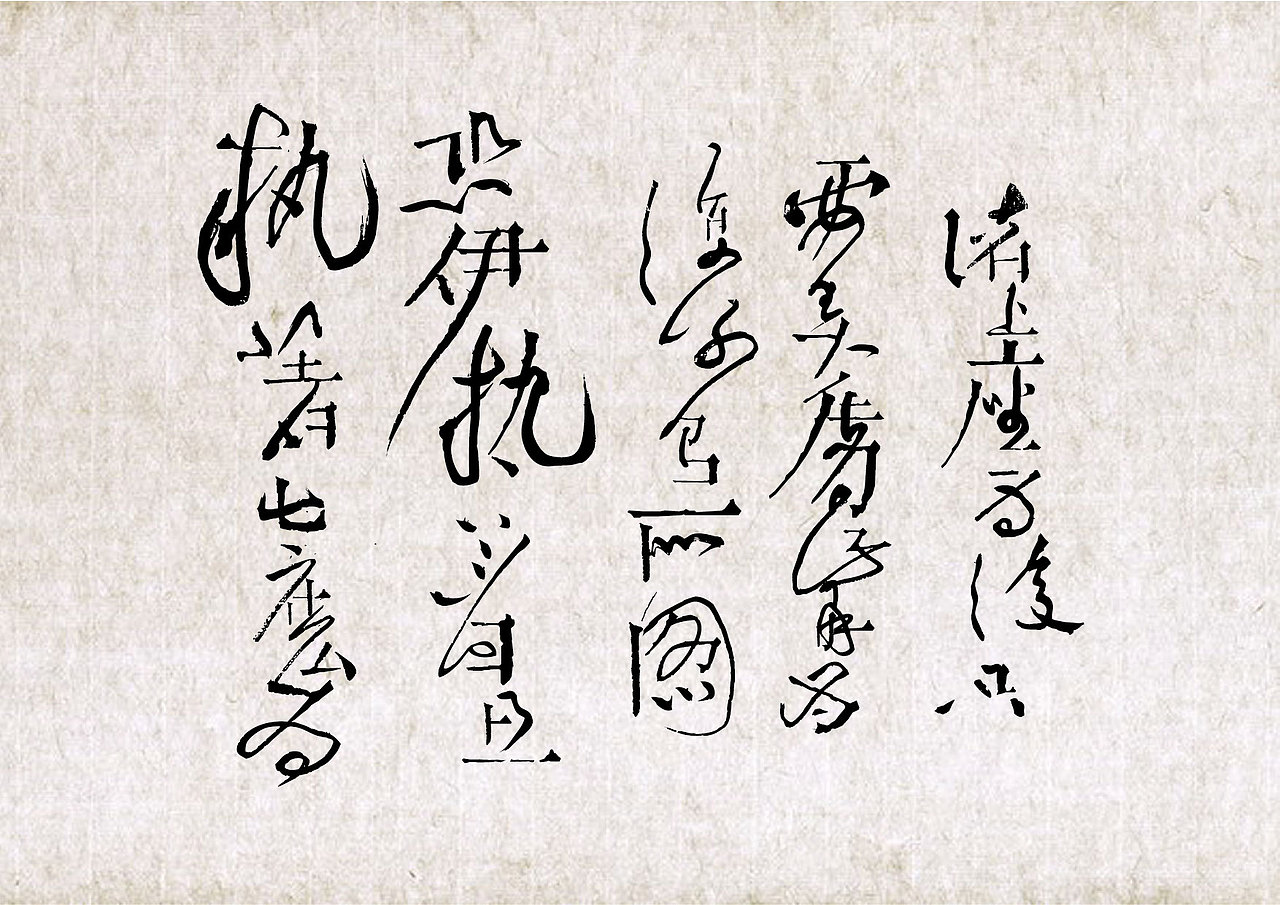
帖宋-宋代书法艺术与字体设计 系列字体设计 延续探索 新帖
《帖宋》宋代书法与字体研究设计 其二_字体设计反思考 《帖宋》课题的第二篇。建立在第一篇章五·帖宋体的设计基础上的反向思考。将宋体笔画嵌入书法名帖字体结构中,将连笔、省笔、代笔等的行字方式进行拆解思考。形成新的文字语言形式探索。新《研山铭》新《陶生帖》新《诸上座帖(节选)》
新《陶生帖》
新《研山铭》
新《诸上座贴》节选